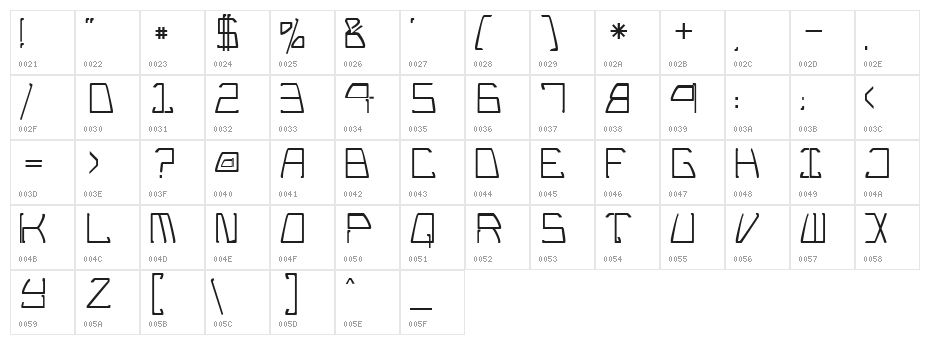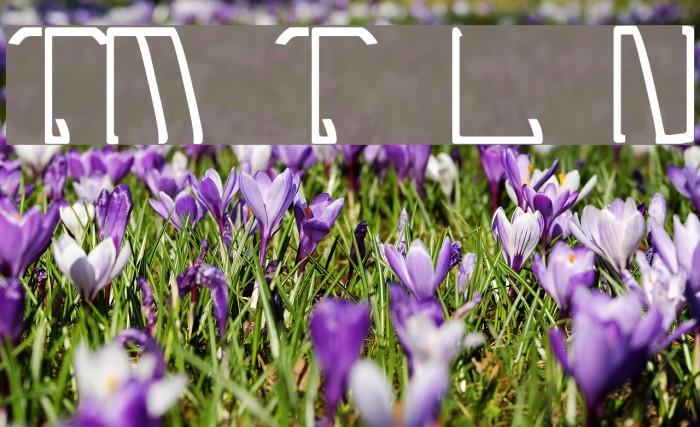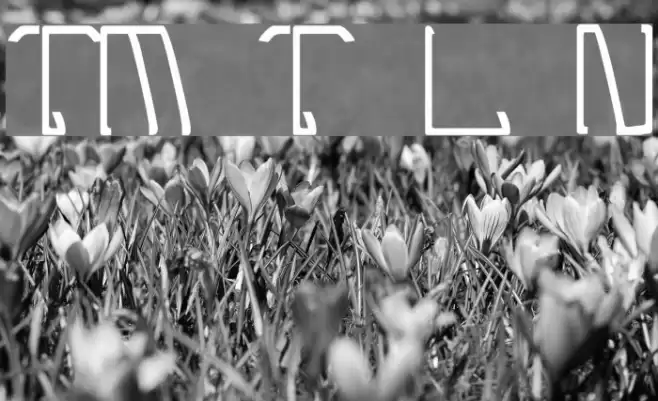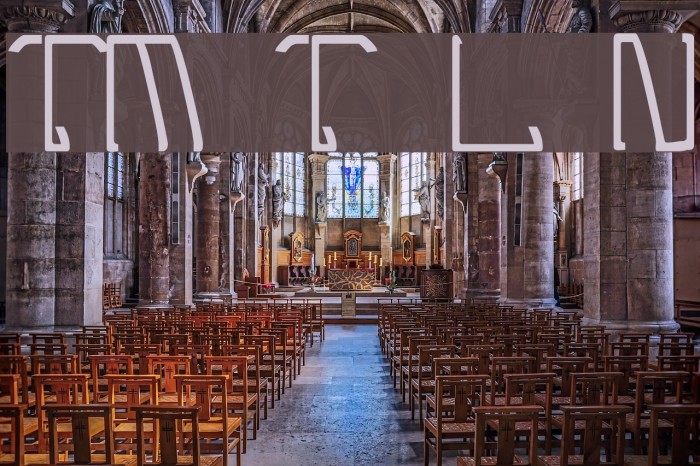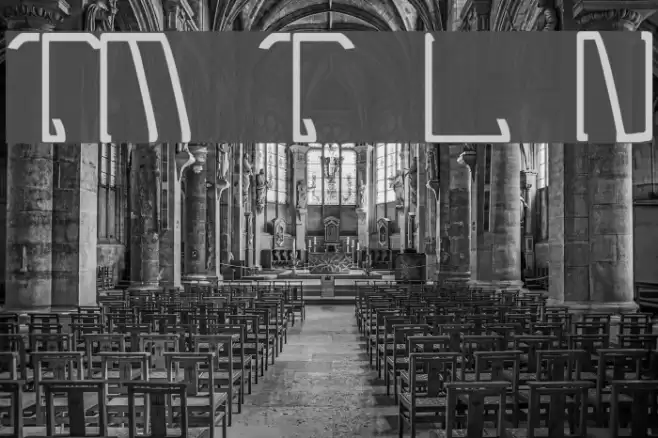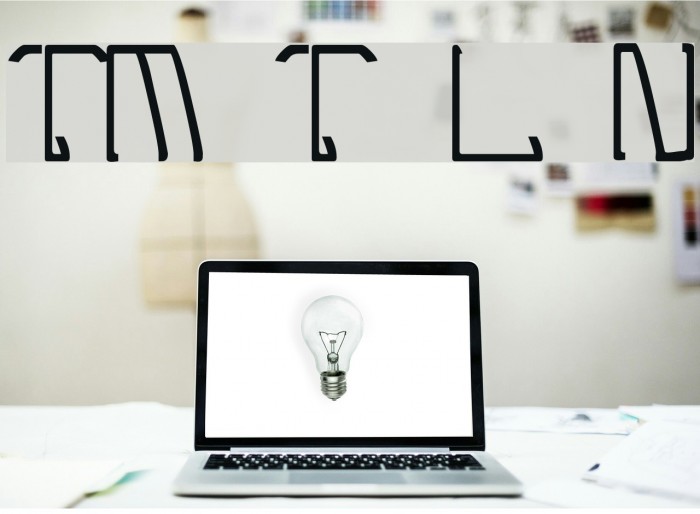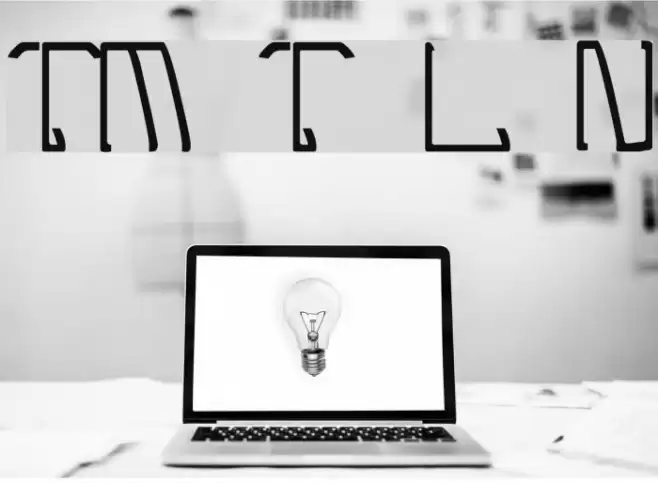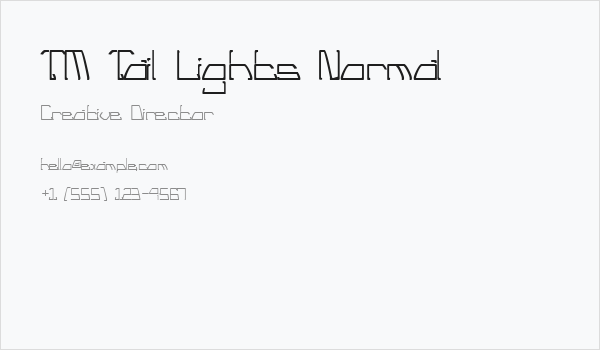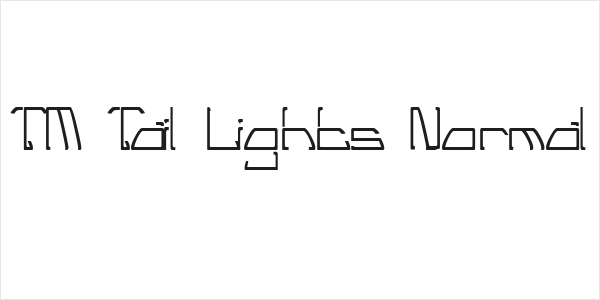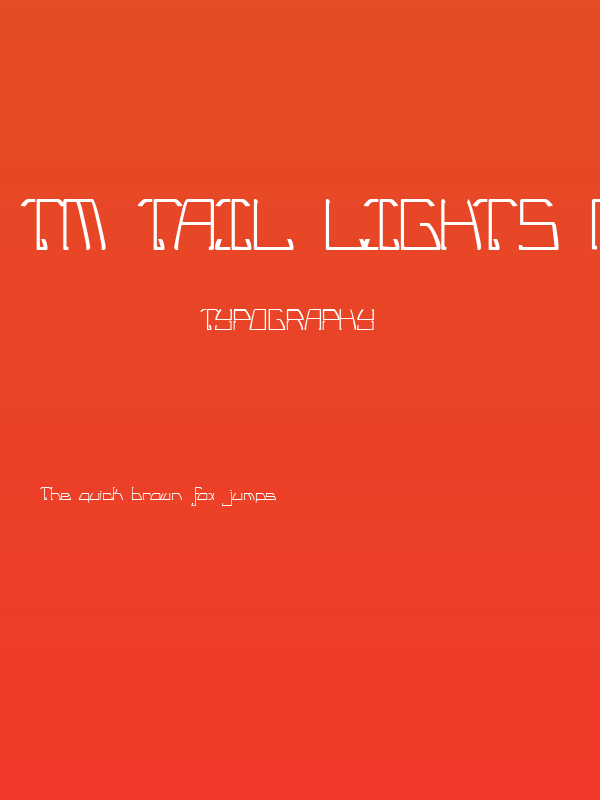
TM Tail Lights Normal Font
| Progetti proposti | Ideal for technology branding, sci-fi themed designs, video game interfaces, and digital art projects. |